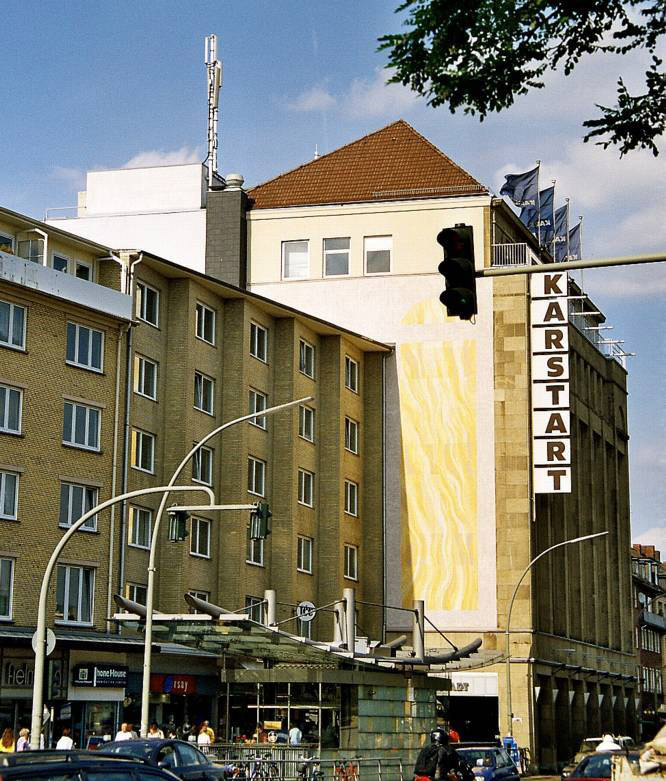
vertikal gesetzt - von oben nach unten
mich würde eure Meinung zu vertikal gesetzter Schrift interessieren. Also nicht wie auf dem Buchrücken sondern von oben nach unten zu lesen.
Ich finde das schwer lesbar und grundsätzlich häßlich. Vielleicht bin ich aber ungerecht.
Gibt es gute Beispiele? „darf“ man das?
Ein Kunde bekommt von seinem Architekten gerade so eine Variante als Hausschrift verpasst. Ich würde es gerne verhindern!
Außer es gibt doch gute Beispiele und ich habe bisher nur verkannt was daran toll sein kann. Ich lasse mich gerne eines bessern belehren.
Ich finde das schwer lesbar und grundsätzlich häßlich.
... ich würde nicht soweitgehen es grundsätzlich hässlich zu finden.
da kmmt vieles zusammen, schriftauswahl, farben und formen.
dazu noch länge des namens etc. das bauhaus bespiel gefällt mir z. b. gut.
das weniger.
aber lass dich mal überraschen was der architekt macht. ;)
Meinst Du Schriften von oben nach unten oder einen Schriftzug 90 Grad gedreht?
Ersteres kann -siehe Beispiel Bauhaus- stiltreu und gelungen enden.
Letzteres ist eine Mode zur Zeit, hier machen das Krankenhäuser, sogar das Polizeipräsidium, auf gewölbten Metallstelen, Fahnen und Logos; ich vermute dahinter tatsächlich Architektenhirne.
RobertMichael hat es treffend formuliert: Schuster und Leisten und so.
Als Nicht-Fachmann finde ich das Querschreiben lästig und albern. Mein Hirn erkennt die langen Wörter nicht sofort, und beim Autofahren den Kopf zu drehen ist nicht Sinn der Sache.
Ich werde mal mit der Kamera auf Jagd gehen, in 10 Jahren schütteln alle den Kopf und wollen nie dabeigewesen sein. (Hoffentlich) :roll:
Möglicherweise ist der Architekt Japaner, dann klappt das schon (gell, Herr Pautner). Oder er hat so gute Beispiele wie Heinrich mit dem Bauhaus. Da funktioniert die Wortlänge mit der Schrift sehr gut.
Gibt es gute Beispiele?
Wenn es eine architektonische Lösung ist, sich also in das Bauwerk stilistisch integriert, und das Bauwerk selbst nach Gestaltungsregeln erbaut wurde, dann ja. Oder es sind chinesische Schriftzeichen.
„darf“ man das?
technisch und in China, ja.
Ein Kunde bekommt von seinem Architekten gerade so eine Variante als Hausschrift verpasst. Ich würde es gerne verhindern!
Wenn es technisch und optisch schlecht umgesetzt wird, waagerecht möglich wäre oder eine Krücke ist, dann kämpfe dagegen an.
Bei gestürzten Linien (90° gedreht) aber auch bei senkrechten Einzelbuchstaben leidet die Lesbarkeit. Bei erstem muss man den Kopf verdrehen und bei letzterem kann es in einem Buchstabierwettbewerb enden. Schnelles Wahrnehmen und Verstehen kann nicht beabsichtigt sein. Dann bleibt die Frage wie CI konform ist das Ganze.
Oder er hat so gute Beispiele wie Heinrich mit dem Bauhaus. Da funktioniert die Wortlänge mit der Schrift sehr gut.
das beispiel ist wirklich gut, denn die schrift passt auch in sich.
das A aufs U das, U ins H, das H aufs A ...
... nur das S fällt etwas raus.
Boa - das Bauhaus-Beispiel ist wirklich gut!
Ich will euch mal den Architekten „Entwurf“ nicht vorenthalten... :-)
(muss das BIld evtl. bald wieder raus nehmen, nur dass ihr euch nicht wundert)
Ich entwickle für das Hotel grade ein Logo und möchte auf keinen Fall, dass dieser Schriftzug (der mit dem Logo gar nichts gemeinsam hat) auf der Fassade steht.
ja, das alte problem.
entweder fragt dich keiner, wenn du ein logo gestalten sollst, dass das
ding auch später mal aufs haus kommt, ob du das in die wege leiten darfst
oder sie wollen den schriftzug vom haus als logo »wir haben schon einen
schriftzug auf unserem haus, den hätten wir gern auf unsere drucksachen«
sowas ist natürlich extrem doof. also versuch dich da auf alle fälle reinzu-
schieben und erkläöre denne wieso DEIN logo dort auf die außenwand muss.
umsetzungsmöglchkeiten dafür gibt es ja genug.
was bedeuten eigentlich diese bänder?
stimmt, lampen. klar.~
ok, eine richtige schrift an der seite (ggf. die logoschrift) ist
ein guter kompromiss. das echte logo kann ja dann aufs vordach
oder auf ein paar flaggen im eingangsbereich.
Momentan sieht es so aus als würde die Stadt die vertikale Schrift nicht genehmigen :-)
Was für ein Pech!! :wink:
Ich finde grundlegend ist gegen senkrechte Beschilderung nichts zu sagen.
Solche Schilder sehe ich irgendwo zwischen Logo und Ornament, das ist
ja kein Fließtext. Lesbarkeit steht hinter Wiedererkennungswert, oder je
nach Anwendung Aufmerksamkeitsheischen zurück.
"Aufmerksamkeitsheischen", hmm, witziges Wortbild, vor allem, wenn ein
Trennprogramm auf die Idee kommt, nach dem ersten Wort umzubrechen...
• 8 Jahre später...
Leider sehe ich immer mehr senkrecht gesetzte Titel oder Überschriften. Es schüttelt mich jedesmal, wenn dies zumindest für mich offensichtlich ohne jede Not geschieht. Entspringt dieses Unwohlsein nur meiner 30 Jahre zurückliegenden typografischen Erziehung? Ist das nur selbstgestrickt und hausbacken von "Ich-kann-das-alleine-Designern" kreiert oder etwa in?
Habt Ihr für mich zitierfährige Quellen, die dieses layouten "verbieten"? Oder muss ich lediglich mit der fehlenden Lesbarkeit argementieren?
Hast du zitierfähige Quellen für "immer mehr senkrecht gesetzte Titel oder Überschriften"?
Mir ist so, als habe ich bei Tschichold etwas dazu gelesen, in den »Erfreulichen Drucksachen«. Aber schlechte Erkennbarkeit zählt doch mehr als ein Zitat, oder?
Bertel, alle persönlichen Eindrücke werden vom Statistischen Bundesamt in der Abteilung Telepathische Privatempirie vollständig und zentral erfaßt und sind dort für jedermann einsehbar, einfach mal dort nachfragen.
Martin, warum so eine persönliche Anmache?
… Aber schlechte Erkennbarkeit zählt doch mehr als ein Zitat, oder?
Fast alle Karstadt-Warenhäuser waren früher so beschriftet und keines davon war "schlecht erkennbar".
Martin, warum so eine persönliche Anmache?
Das war keine »Anmache«, sondern eine scherzhafte Replik auf deine »Frage« nach »zitierfähigen Quellen« für einen persönlichen Eindruck.
Aus gutem Grund werden höchstens Wörter wie KINO vernünftigerweise vertikal gesetzt. Wenn man »Karstadt« einmal buchstabiert hat, erkennt man es ja wieder, das muß man nicht mehr »lesen«. Aber alle Veränderungen der Leserichtung behindern den Lesefluß, das dürfte wohl nicht
f
r
a
g
l
i
c
h
sein.
Dafür, dass du gar nicht genau weißt, von was MacSchneck eigentlich spricht, lehnst du dich mit deinen Aussagen zu "Aus gutem Grund" und "vernünftigerweise" grad ziemlich weit aus dem Fenster. Gerade Karstadt ist der beste Beweis dafür, dass "aus gutem Grund" und "vernünftigerweise" vertikal Gesetztes gut aussieht und lesbar ist.
Spielt da nicht die Gewohnheit und Übung eine große Rolle? Haben Japaner Probleme mit Vertikalsatz?
Man müsste mal ein Jahr lang jeden Tag eine DinA4-Seite im Vertikalsatz lesen. Denke, dass man dann mit Lesbarkeit keine Probleme mehr hat. Auch wird man dann Wortbilder erfassen und nicht mehr einzelne Buchstaben entziffern und zu Wörtern kombinieren.
Denke ich auch, die Japaner würden wahrscheinlich nicht schneller lesen, wenn sich in ihrem Schriftsystem eine horizontale Satzanordnung durchgesetzt hätte.
Edit: Aber eigentlich geht es um ein Logo, was ich nicht sehen konnte, weil es leider ganz schnell wieder gelöscht wurde.